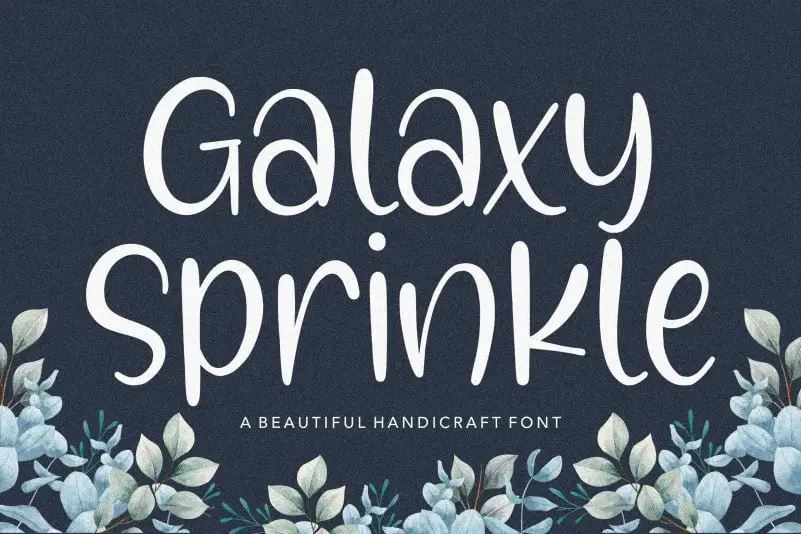
Galaxy Sprinkle Beautiful Handcraft Font – Download Grátis
A fonte “Galaxy Sprinkle Beautiful Handcraft Font” é uma escolha perfeita para qualquer projeto que precisa de uma mão-dupla artesanal e elegante, combinando elementos de arte manual com um toque delicado e refinado. Desenvolvida pelo designer balpirick, essa fonte idealmente se adapta a vários usos, desde o design do produto até a criação de conteúdo para blogs e revistas. Seu estilo fluido e orgânico é especialmente adequado para trabalhos que valorizam uma aparência cuidadosamente pensada e personalizada. Ainda não há informações específicas sobre as aplicações práticas neste projeto, mas podemos inferir que ela poderia ser perfeita para criação de logotipos de marcas ou projetos de identidade visual, por exemplo. Suas formas suaves e seus traços delicados permitem uma expressão única para os textos de marca, tornando-a ideal para a estética sofisticada dos produtos de luxo ou eventos sociais como casamentos. O uso da fonte em projetos digitais também pode ser muito prático. Suas formas fluidas e sua tipografia elegante permitem um resultado final que se adapta bem à web, mantendo o estilo elegante mesmo ao passar por filtros de imagens online. Essa é uma fonte versátil e convidativa que certamente enriqueceria qualquer projeto de design visual.